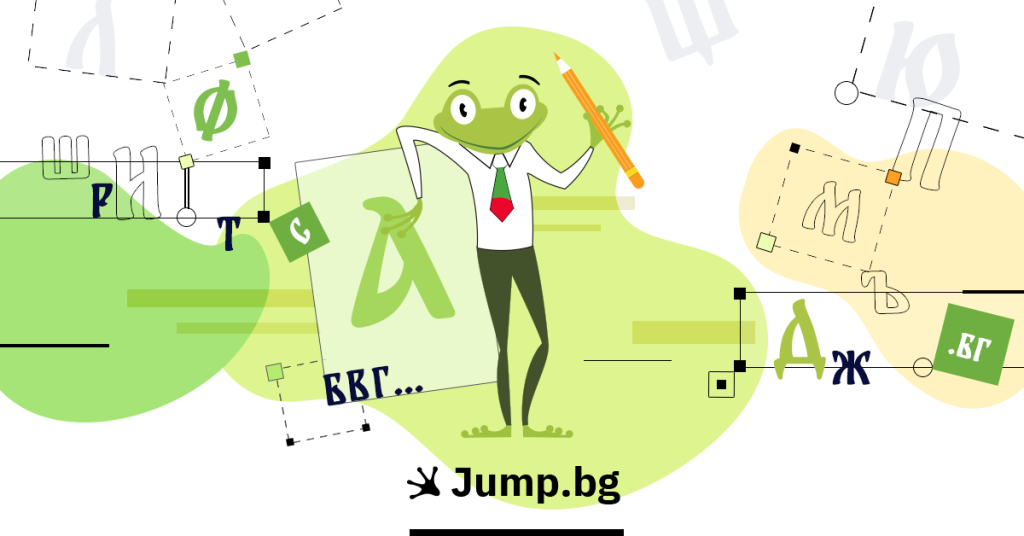
За „българската кирилица“ и шрифтовете, които я поддържат
В публикацията ще разгледаме - що е то „българска кирилица“, по-популярните шрифтове, които я поддържат или са с по-обла форма, в т.ч. с имена на градове, дигитализацията на почерците на Ботев и Левски и още интересни и полезни факти и обстоятелства по темата.
Създаването на единна писмена система, като кирилицата, има огромно значение за развитието на книжовността, културата и самосъзнанието на българите и останалите славянски народи.
Кирилицата е резултат от дълга и сложна история на промени и адаптации. Първоначално светите братя Кирил и Методий създават глаголицата, а по-късно Климент Охридски, ученик на Кирил, разработва кирилицата. Тези две азбуки имат решаващо значение за развитието на писмеността и културата на славянските народи.
В контекста на кирилицата и шрифтовете, които я поддържат, е важно да споменем още две значими фигури, дали значителен тласък на кирилицата, а именно руският цар и впоследствие император Петър Първи (известен още като Петър Велики), и германският изобретател Йоханес Гутенберг.
В средата на 15 век, Йоханес Гутенберг разработва свое изобретение, което представя през общността като печатарска машина. Тя много бързо влиза в употреба и води до значително улеснение в производството на книги и разпространението на информация, като през 17-18 век, по време на управлението на тогавашното Руско царство (впоследствие Руска империя), Петър Първи осъществява важни реформи и модернизации. Той проявява изключителен интерес към практиките и технологиите, които се развиват в Западна Европа, като още през 1708 г. предприема революционна реформа, адаптирайки буквите от кирилицата към начина, по който се изписват латинските, за да могат по-лесно и бързо да се печатат текстове на кирилица с революционната машина на Гутенберг.
Въпреки че Гутенберг не е пряко свързан с азбуката, неговото технологично откритие е от огромно значение в онези времена, защото това е първата механично задвижвана печатна преса с ръчен набор от метални букви.
Възможността да се печатат книги на кирилица насърчава разпространението на книги и научни публикации, написани на кирилица и допринася за укрепването на българската култура и самосъзнание.
Така, освен създаването на кирилицата - важен етап в нашата история, революционното откритие на Йохан Гутенберг и реформата на Петър I дават тласък в развитието на нашата писменост, култура и самосъзнание, както и в тези на останалите славянски народи, оставят траен отпечатък и запазват и разширяват нашето общо културно наследство и идентичност през вековете.
Що е то „българска кирилица“?
В интернет пространството днес често срещаме термините „българска кирилица“ и „българска форма на кирилицата“. Те означават едно и също нещо и се отнасят за точно определена форма на изписване на буквите в азбуката.
В следното изображение може да видите разликите в изписването на буквите:
Сравнение между традиционна и българска кирилица
В кирилицата, която всички познаваме, както главните, така и малките букви, се изписват печатно и изглеждат по един и същ начин, с изключение на това, че едните са главни, а другите - малки.
Обаче, когато използваме наклонена форма на буквите или терминологично казано - курсивен вариант, визуално получаваме това, което се вижда в дясната страна на изображението по-горе. Днес ненаклонената версия с обли форми наричаме просто „българска кирилица“, но нека навлезем в детайли.
За изненада на мнозина - в официалния правописен речник на съвременния български книжовен език такова разграничаване във формите на буквите не съществува. Това е предпоставка хората да дават различни становища за произхода им - в повечето случаи дори несъстоятелни.
В тази статия не целим да правим внушения как е най-правилно да ги наричаме, а да покажем, че ги има и че могат да се използват в ежедневието. Най-вероятно Вие вече ги използвате по един или друг начин на мобилните си телефони и таблети, но не сте обърнали внимание.
Според професионалисти в областта на типографията, са нужни сериозни теоретични изследвания и научна основа, за да се даде официално название на въпросните форми, а след това е отговорност на Института за български език към БАН да впише решението в официалния правописен речник на съвременния български книжовен език.
Докато отговорните лица се опитват (или пък не?) да излязат с официално становище, то водещи световни компании успешно внедряват тези форми в шрифтовете си. Най-често се определят, като алтернативна форма на кирилицата или дори като обла или овална форма на кирилицата. И в това има логика.